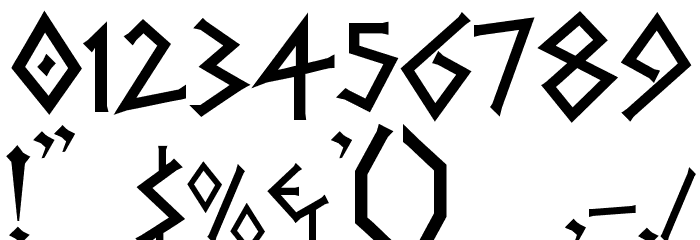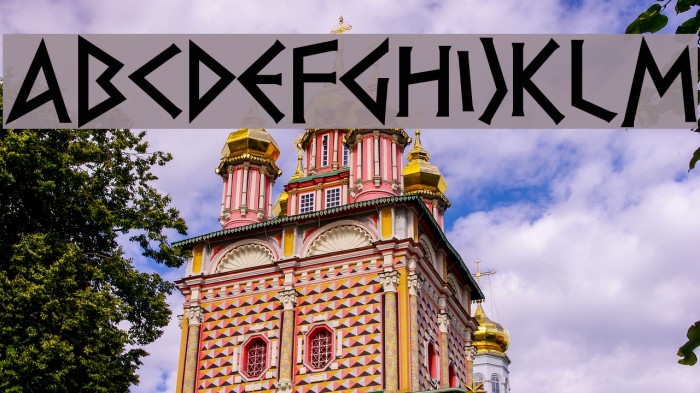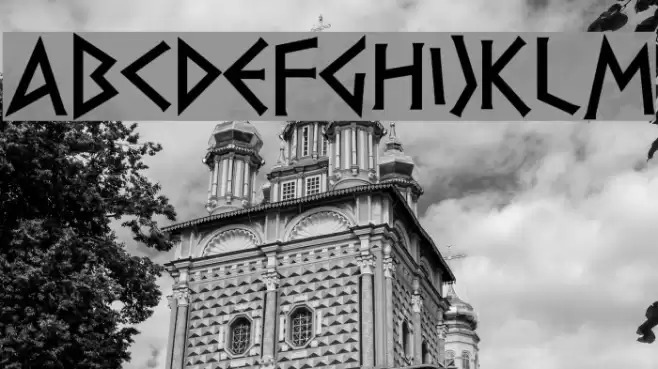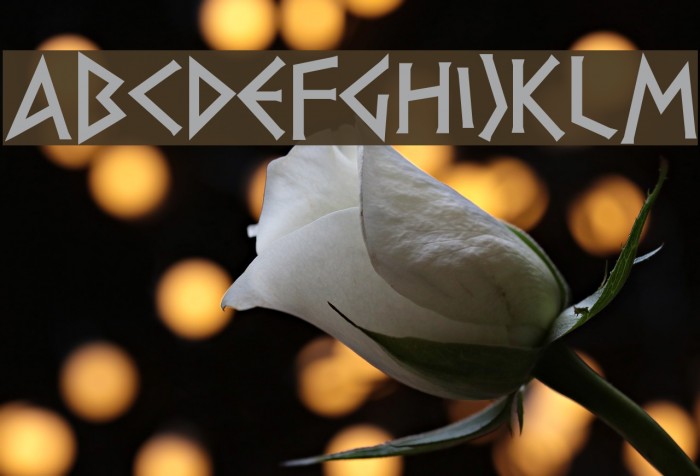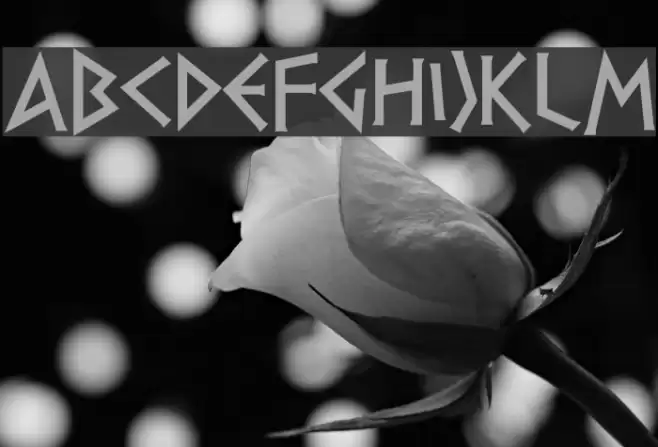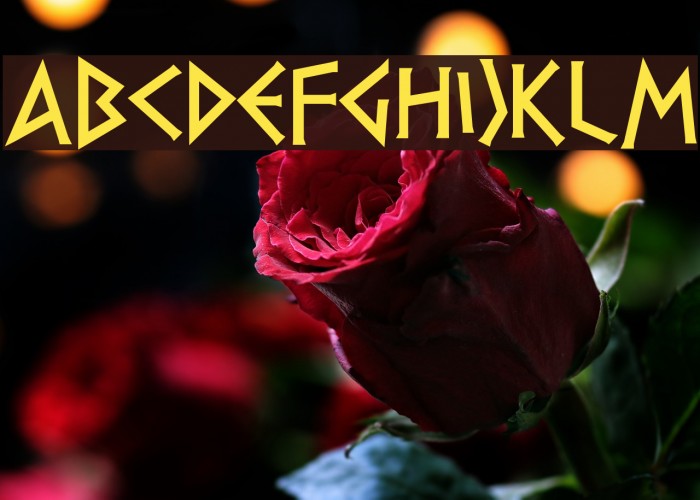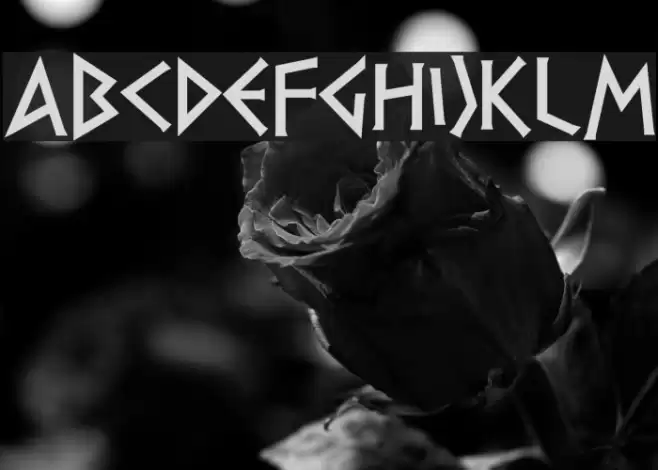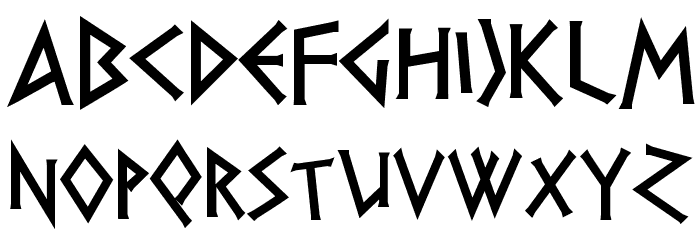
DS Greece Font
| Vorgeschlagene Projekte | Ideal for projects that require a historical or cultural theme, such as museum exhibits, educational materials, or themed event branding. |